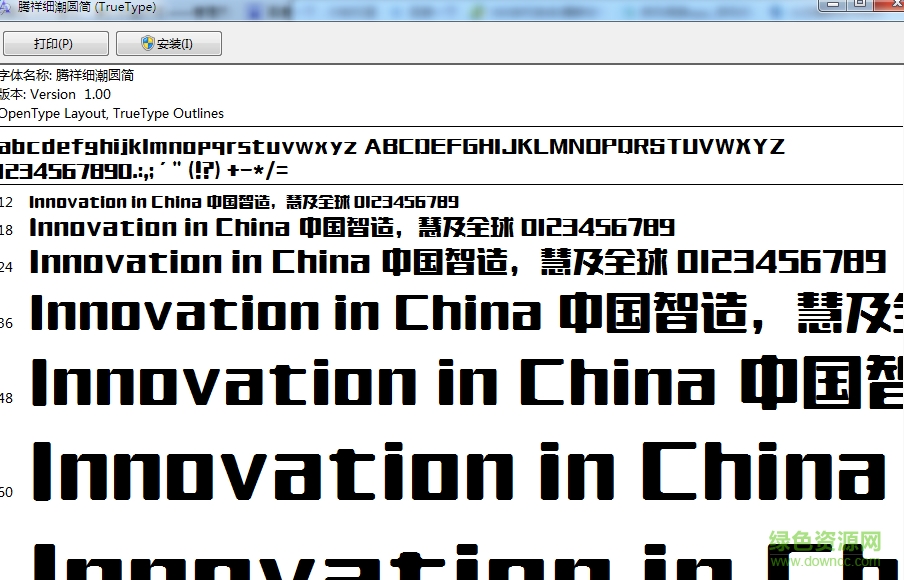
騰祥細潮圓簡是一款筆畫簡潔圓潤的電腦字體,在細微處變換靈動,即實用又富有裝飾效果,且清晰易讀。適合標題和屏顯用字,可用于印刷出版、包裝設計、廣告設計、網頁設計、屏幕顯示等。有需要就來綠色資源網下載!
騰祥細潮圓字體是在細潮黑基礎上變換設計而成。細潮圓將細潮黑的棱角柔化形成被融化之感,融化了的筆畫圓潤富于親和力。字形結構扁方、端莊,橫豎筆畫粗細比例適度、豎筆粗壯有力,布白均勻、行文貫通。